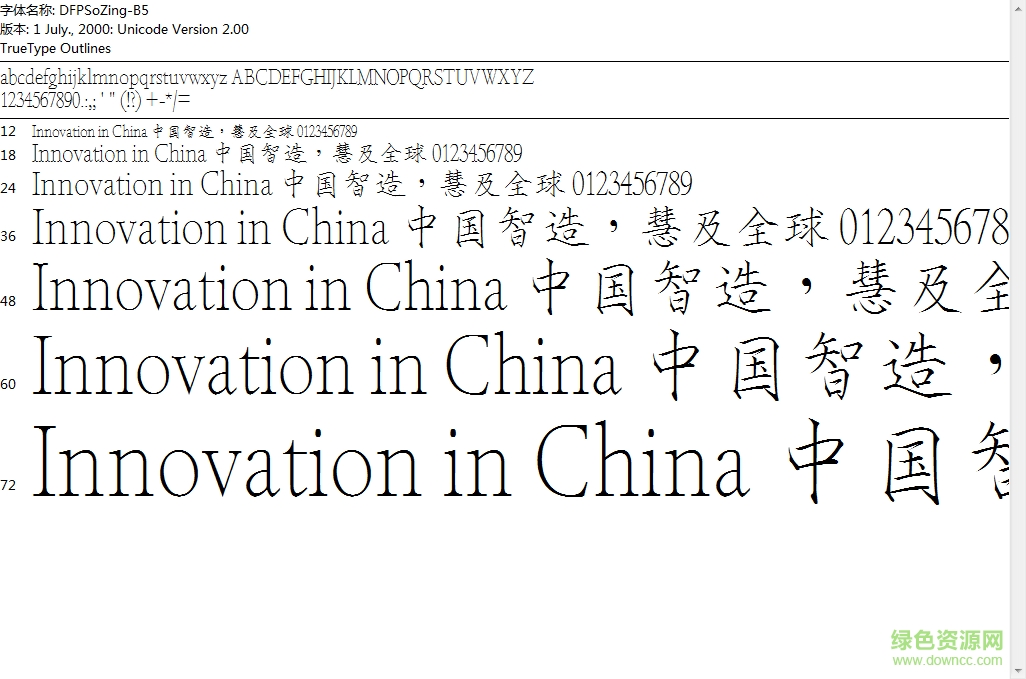
吳邪瘦金體
吳邪瘦金體字體是一款ttf格式的瘦金字體,盜墓筆記里吳邪所寫(xiě)的筆記就是用的這種字體,線條干凈,筆鋒犀利有傲骨,大氣美觀,也是書(shū)法家們常用的字體之一,喜歡文章創(chuàng)作的朋友們可以考慮一下,歡迎登陸綠色資源網(wǎng)進(jìn)行下載安裝哦。
瘦金體特點(diǎn)
瘦金體運(yùn)筆靈動(dòng)快捷,筆跡瘦勁,至瘦而不失其肉,其大字尤可見(jiàn)風(fēng)姿綽約處。因其筆畫(huà)相對(duì)瘦硬,故筆法外露,可明顯見(jiàn)到運(yùn)轉(zhuǎn)提頓等運(yùn)筆痕跡,是一種風(fēng)格相當(dāng)獨(dú)特的字體。